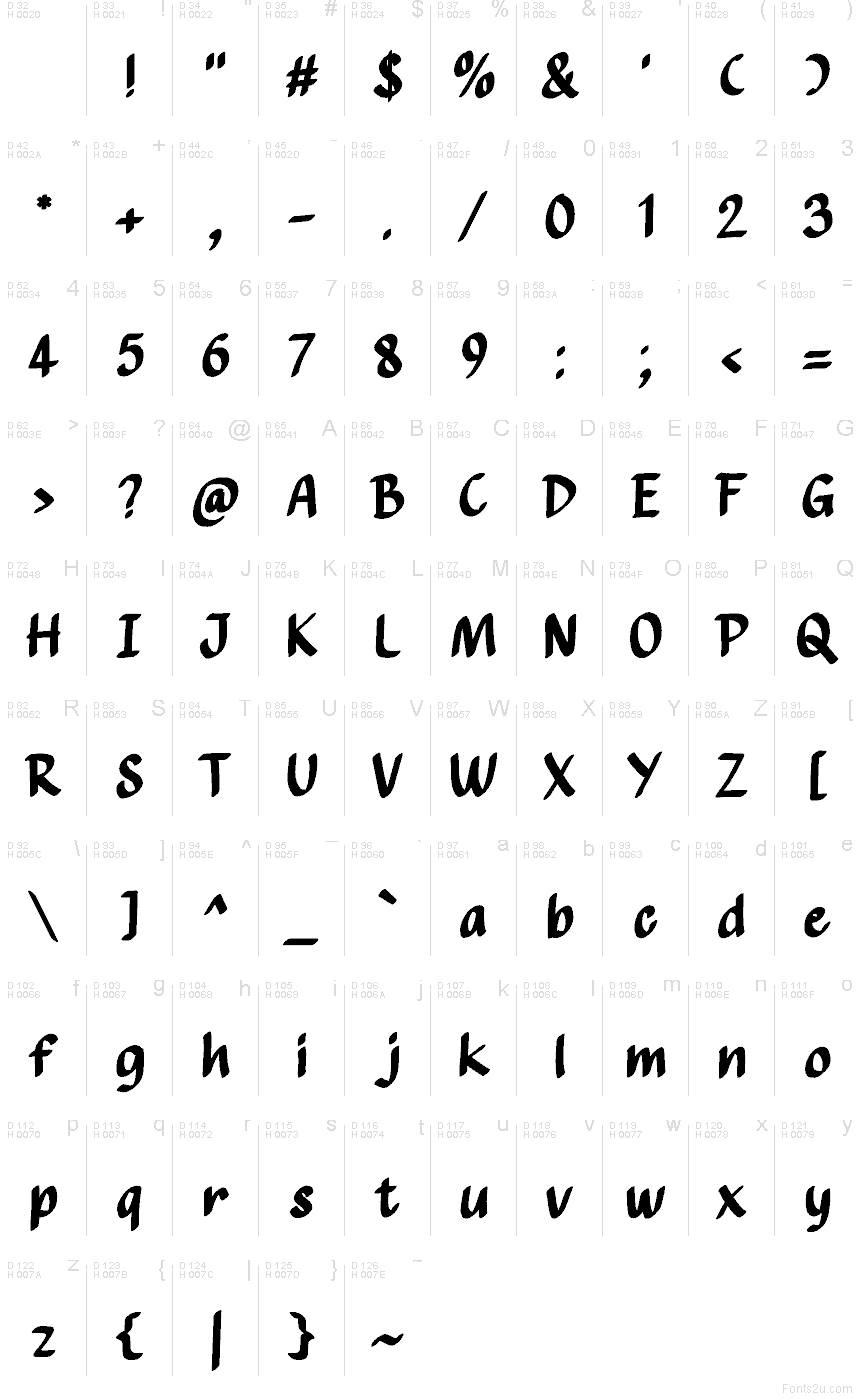
General Komik
General Komik від Hello Good Studio - це безкоштовний коміксний шрифт для заголовків із заокругленими штрихами, що нагадують пензель, та живим рукописним ритмом. Літери поєднуються вільно та плавно вигинаються в м’які петлі, надаючи шрифту невимушеного, дружнього характеру, без жодної скутості чи формальності.
General Komik чудово підходить для логотипів, заголовків на плакатах, дитячого пакування, коміксних хмаринок та грайливої графіки для соцмереж. Цей безкоштовний шрифт додає рукописної виразності, яка ідеально пасує для коротких текстів, декоративного брендингу, листівок та будь-яких макетів, що потребують легкого, казкового настрою.